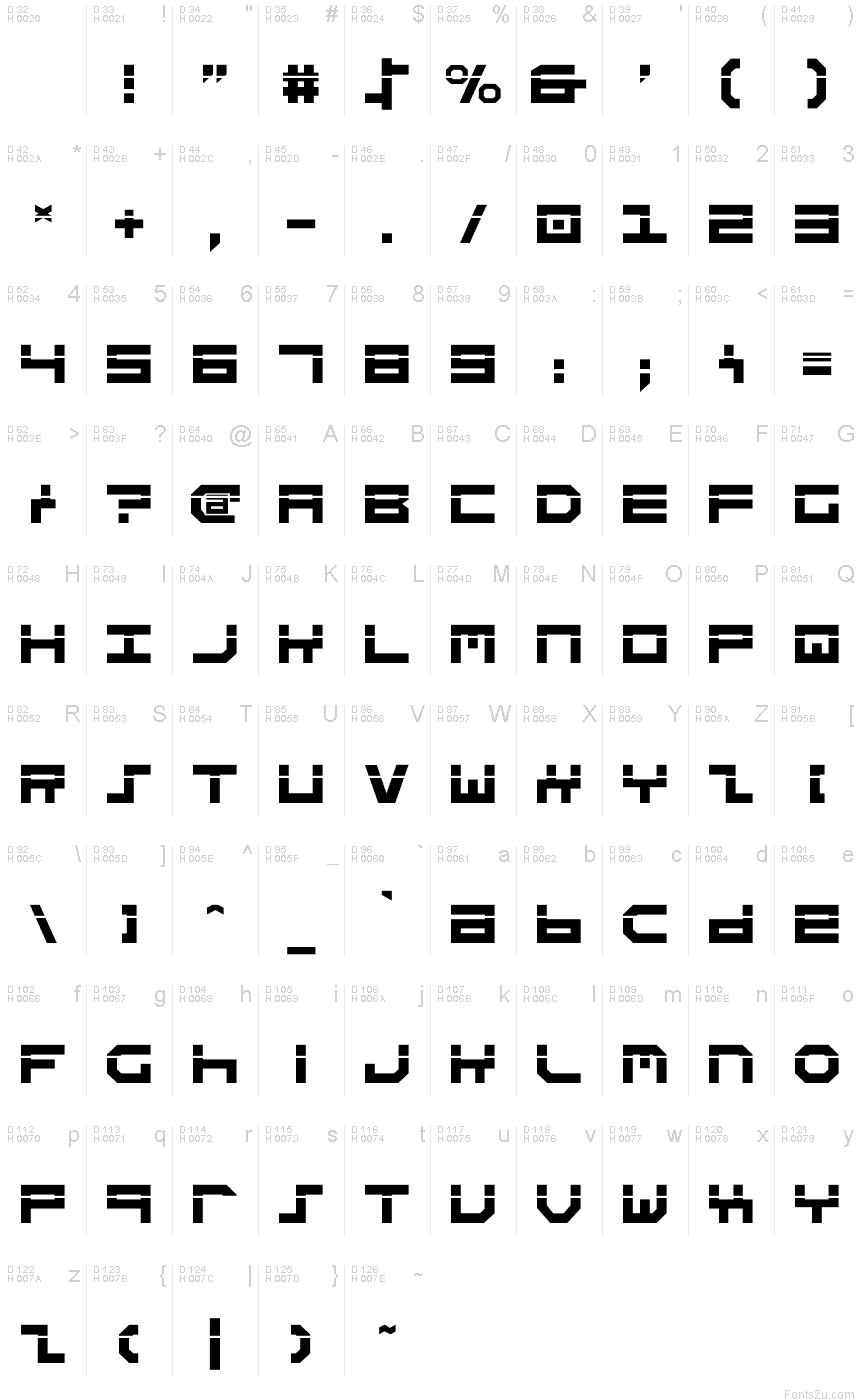
Stuntman Laser هو خط عرض مستقبلي مجاني بأسلوب القوالب (Stencil) من Iconian Font، يجسد طابع الخيال العلمي الحاد الذي نراه في ألعاب الآركيد وتصاميم الأكشن. الحروف عريضة ومربعة ومقسمة بحدة، مع زوايا مقصوصة وكسرة أفقية قوية تجعل التصميم يبدو وكأنه أجزاء من آلة أو درع أو لافتات مقصوصة بالليزر.
يتناسب هذا الخط بشكل طبيعي مع شعارات الألعاب، وعناوين الملصقات، وأغلفة القصص المصورة، وبطاقات العناوين، وتصاميم الفعاليات التقنية حيث تتطلب الكلمات القصيرة تأثيراً سينمائياً قوياً. وبما أنه خط مجاني، فهو مثالي أيضاً للشارات (Badges) والمونوغرامات وتصاميم المنتجات، لأن هندسته المقطوعة تمنح حتى الحروف القليلة مظهراً مدروساً وبنيوياً.